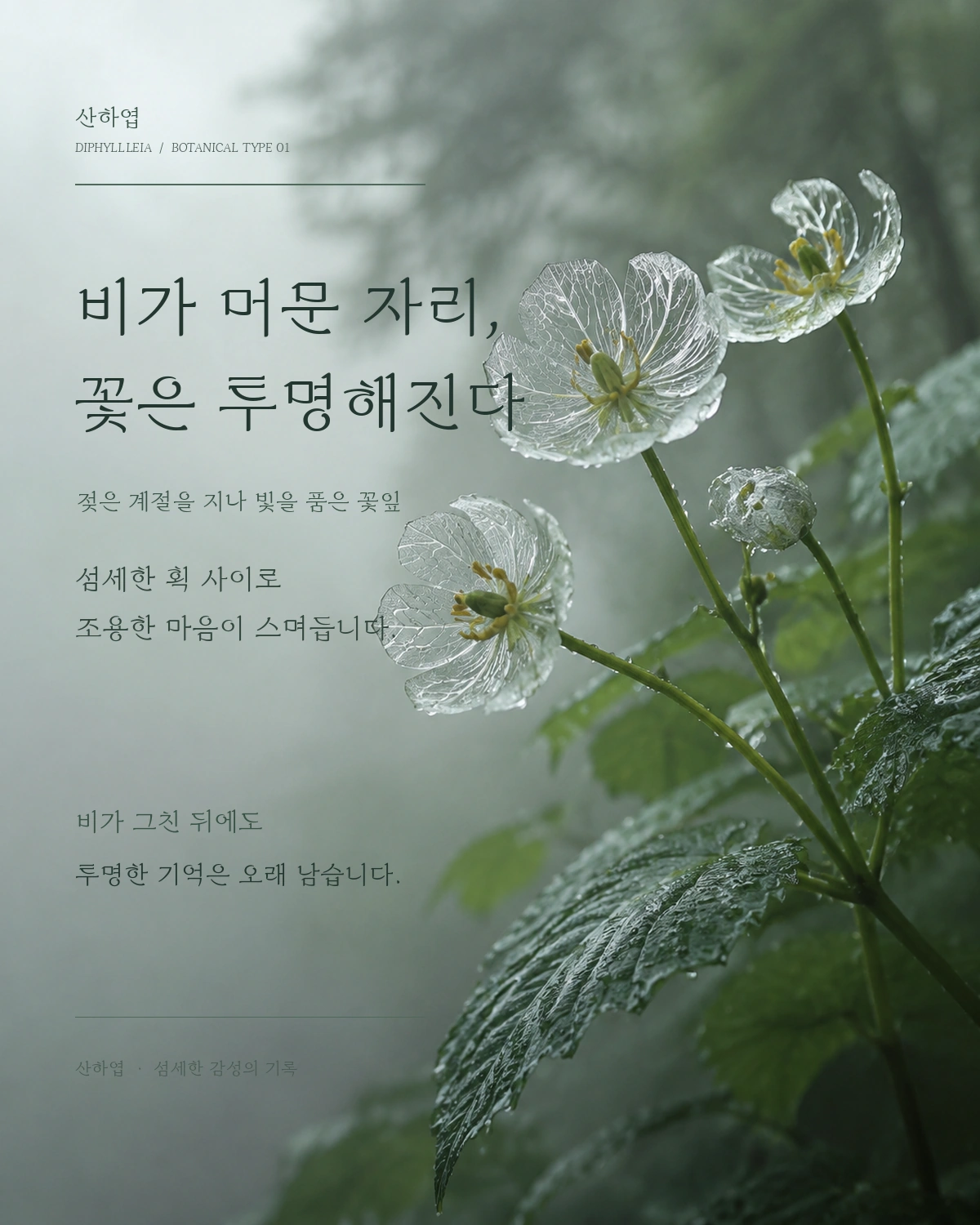
산하엽 — Hyungminha, Jamo에서 배포하는 무료 폰트입니다. 비를 맞으면 꽃잎이 투명해지는 식물의 정서를, 붓의 결로 옮겨 담은 섬세한 세리프 서체
이 서체에는 겹겹의 이야기가 있습니다. 형민하가 자모라는 이름으로 2022년에 만들었고, 출발점은 샤이니 종현의 곡 산하엽입니다. 그리고 그 곡의 제목인 산하엽은 비를 맞으면 꽃잎이 투명해지는 식물의 이름입니다. 꽃에서 노래로, 노래에서 글자로 이어진 셈입니다.
제작자는 그 정서를 붓 느낌의 획으로 옮겼습니다. 다만 연약함만 표현한 것은 아니라고 밝혔습니다. 가늘고 생략된 획에 점차 두꺼워지는 요소를 섞어, 부드럽지만 강한 꽃의 인상을 담으려 했다는 것입니다.
쓰는 자리에 대한 제작자의 말이 눈에 띕니다. 제목용으로도 좋지만 부드럽게 다듬은 곡선 덕분에 오히려 긴 본문에서 효과적이며, 읽는 사람이 전체적인 인상을 음미할 수 있다고 했습니다. 굵기는 하나뿐이라 위계는 크기로 만들어야 합니다. 한글은 2,781자이고 오픈 폰트 라이선스로 배포되어 수정과 재배포가 자유롭습니다.